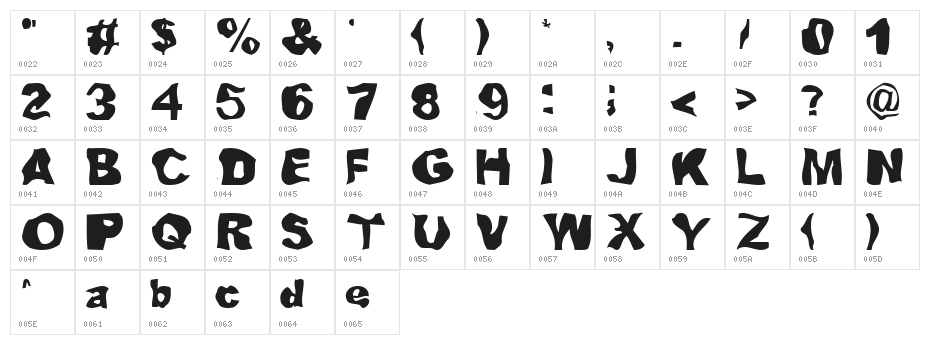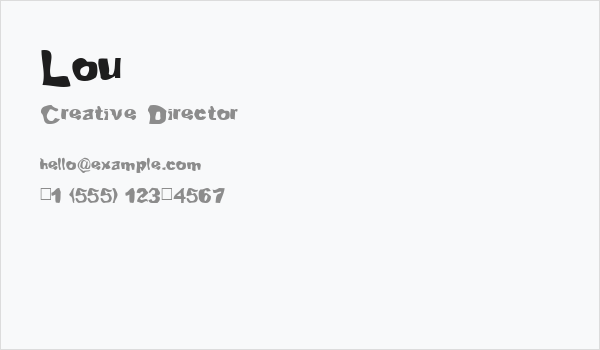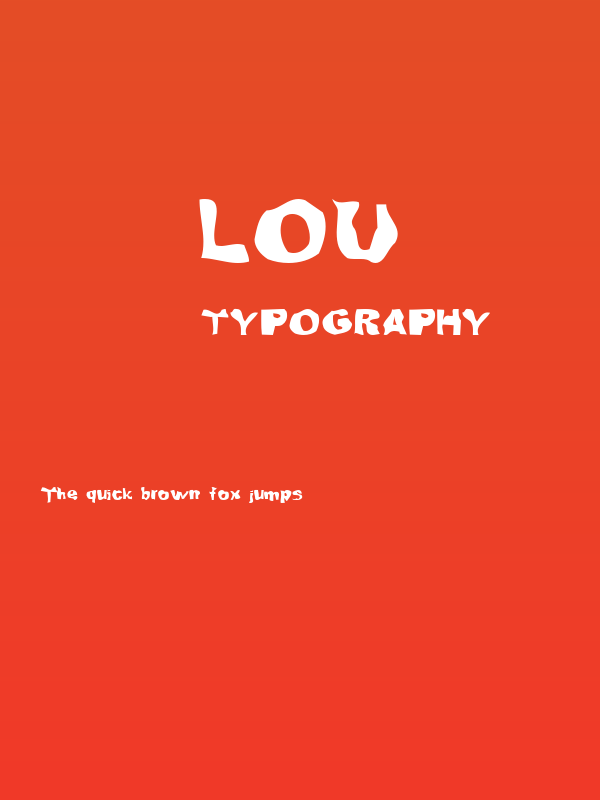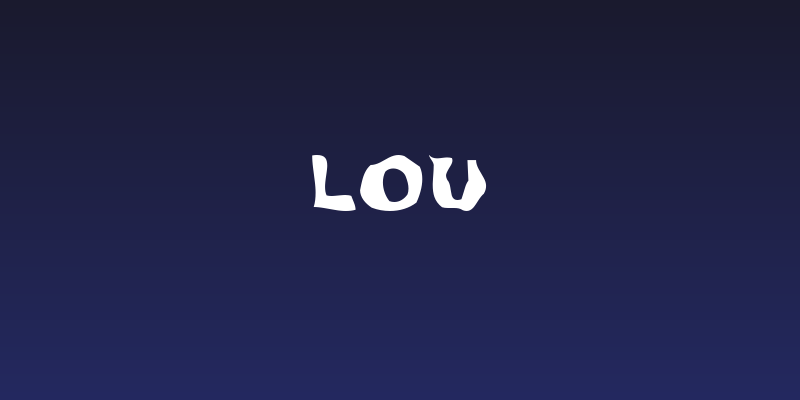
Lou Font
يتضمن هذا الخط 89 حرفًا. انقر على أي حرف لرؤية التفاصيل.
| النمط العام | Playful, Whimsical, Hand-drawn |
| مشاريع مقترحة | Ideal for children's books, playful branding, party invitations, and creative posters. |